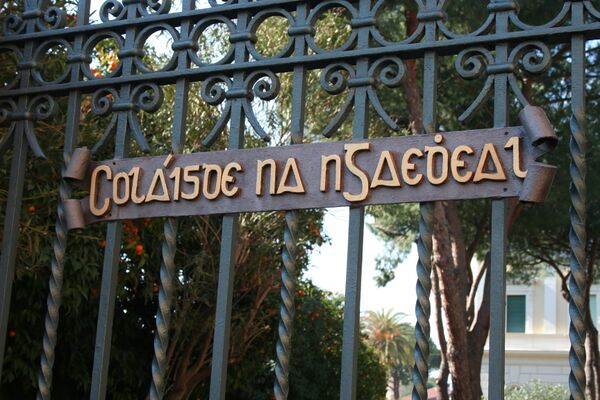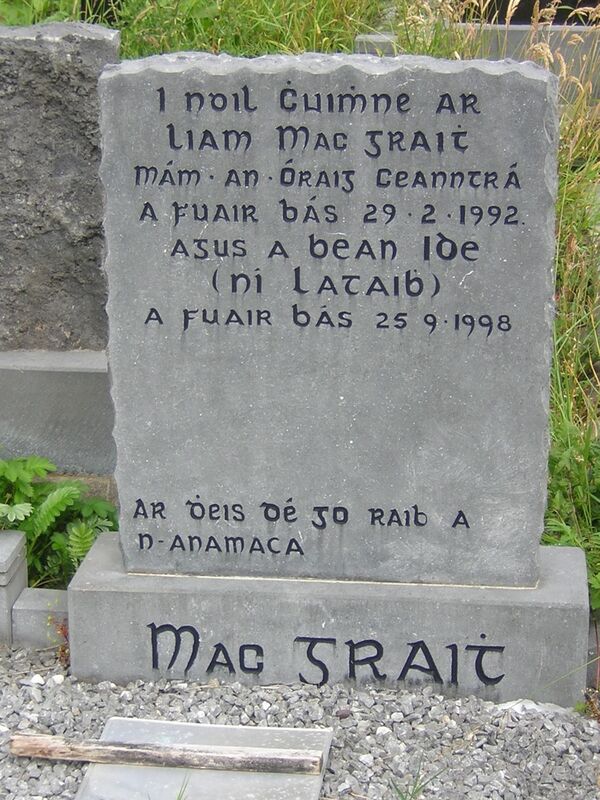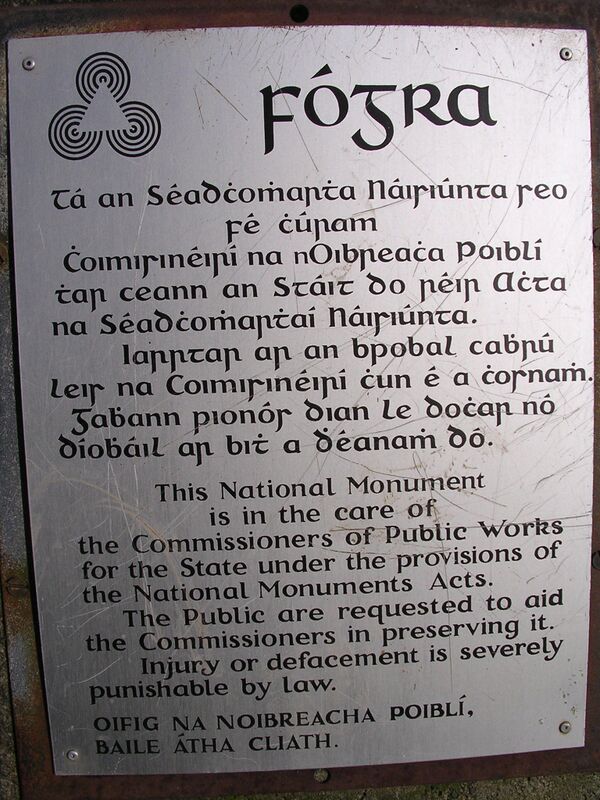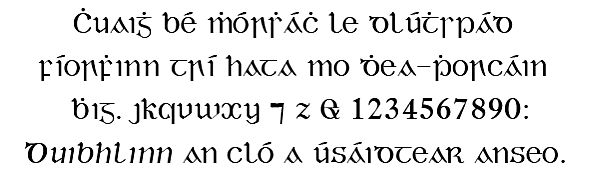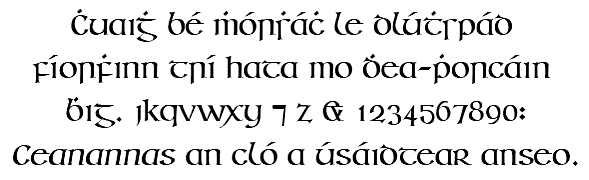
Гэльский шрифт
Гэльский шрифт (ирл. cló Gaelach — [kɫ̪oː ˈɡeːɫ̪əx]) — термин, которым обозначают семью островных шрифтов, разработанных для записи ирландского языка. Их использовали в XVI—XX вв. Иногда все гэльские шрифты называют «кельтскими» или унциальными, хотя большинство гэльских шрифтов не являются унциальными. В Ирландии термин «cló Gaelach» употребляют как противоположный термину «cló Rómhánach» (романский шрифт). Иногда гэльский шрифт называют ирландским. «Англосаксонский» шрифт XVII в. принадлежит к этой категории, поскольку он, как и гэльский/ирландский, происходит от рукописных шрифтов Ирландии.
Характеристика
Кроме 26 букв латинского алфавита, гэльский шрифт должен содержать все гласные с острым ударением (Áá, Éé, Íí, Óó, Úú); набор согласных с точкой сверху (Ḃḃ, Ċċ, Ḋḋ, Ḟḟ, Ġġ, Ṁṁ, Ṗṗ, Ṡṡ, Ṫṫ), а также тиронский знак et — «⁊», который в ирландском языке употребляют вместо союза agus («и»). Гэльские шрифты также часто содержат островные формы букв s и r, а некоторые — также лигатуры, которые употребляли в ранних гэльских рукописных текстах. Малую букву i пишут без точки, а буквы d, f, g и t имеют «островные» формы. Много современных гэльских шрифтов содержат формы букв j, k, q, v, w, x, y и z, а также поддерживают гласные, которые употребляют в других кельтских языках. Они также различают знаки «&» и «⁊», хотя некоторые современные шрифты последовательно заменяют амперсанд тиронским знаком, поскольку оба означают союз «и».
Происхождение
Ирландский унциальный алфавит происходит от средневековых рукописей как «островной» вариант латинского письма. Первый гэльский шрифт был создан в 1571 году для использования в катехизисе, что должно было способствовать обращению ирландцев к протестантству, чего добивалась английская королева Елизавета I.
Использование
Печать этим шрифтом была общепринята в Ирландии до середины XX века. Сегодня же его используют преимущественно для декоративных целей; например, немало ирландских газет печатают свои названия на обложке гэльским шрифтом, а также он популярен в названиях пабов, поздравительных открытках и в рекламе. Эдвард Ллуйд в своем труде о грамматике корнского языка использует согласные из гэльского шрифта для обозначения звуков [ð] и [θ].
Гэльский шрифт в Юникоде
Юникод относит гэльский шрифт к вариантам латинского алфавита. Малая островная буква g (ᵹ) была добавлена в версии 4.1 как часть Phonetic Extensions block, поскольку ирландские языковеды используют её для обозначения звука [ɣ]. Unicode 5.1 (2008) впоследствии добавил букву G (Ᵹ), а также большую и малую буквы D, F, R, S, T; обратная островная g была добавлена, поскольку Эдвард Ллуйд принял её в своем труде «Archaeologia Britannica» (1707 г.) для научного правописания корнского языка.
- Ᵹ ᵹ островная G (U+A77D, U+1D79)
- Ꝺ ꝺ островная D (U+A779, U+A77A)
- Ꝼ ꝼ островная F (U+A77B, U+A77C)
- Ꝿ ꝿ перевёрнутая островная G (U+A77E, U+A77F)
- Ꞃ ꞃ островная R (U+A782, U+A783)
- Ꞅ ꞅ островная S (U+A784, U+A785)
- Ꞇ ꞇ островная T (U+A786, U+A787)
Примеры
Chuaigh bé mhórshách le dlúthspád fíorfhinn trí hata mo dhea-phorcáin bhig,
Ċuaiġ bé ṁórsháċ le dlúṫspád fíorḟinn trí hata mo ḋea-ṗorcáin ḃig,
что означает «Очень довольная женщина пошла с действительно белой лопатой через шляпу моей маленькой хорошо упитанной свиньи».
Второе предложение:
Duibhlinn/Ceanannas an cló a úsáidtear anseo,
что означает «Duibhlinn / Ceannanas является шрифтом, который здесь использовали».
Во втором предложении употреблены короткие формы букв r и s; а в первом — длинные.